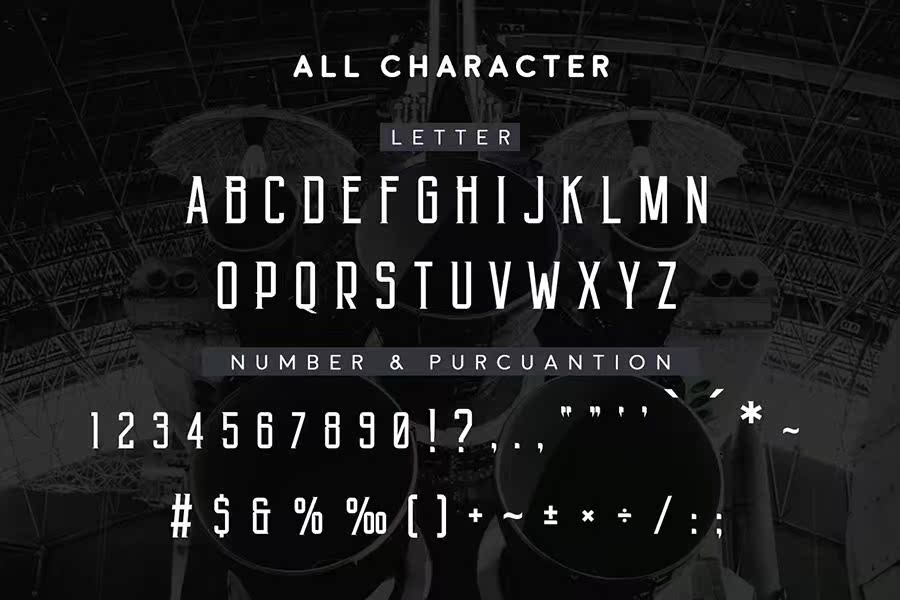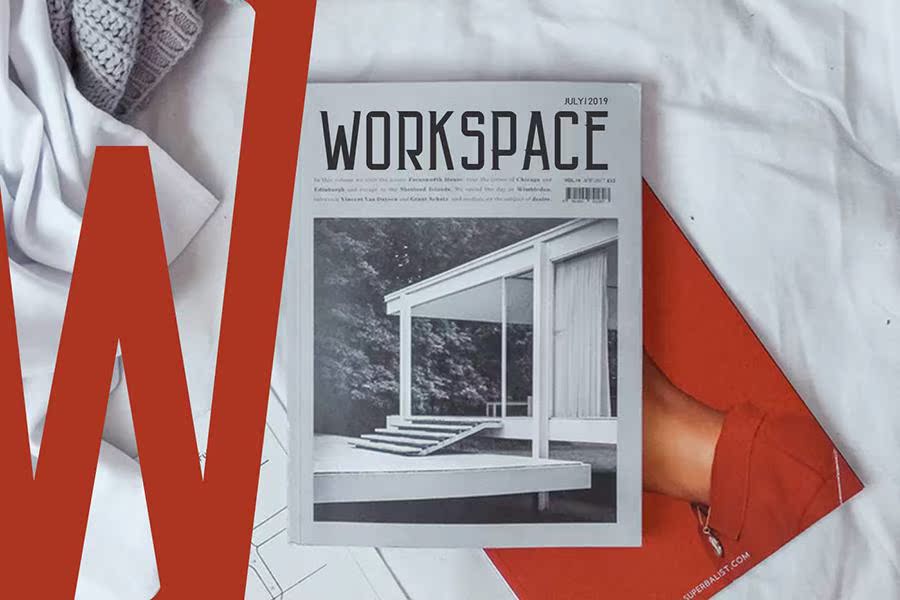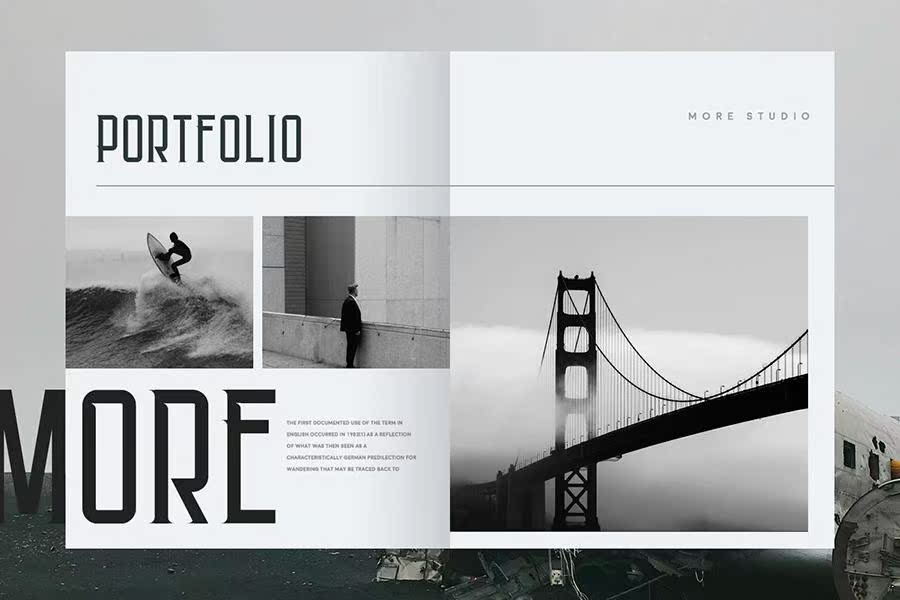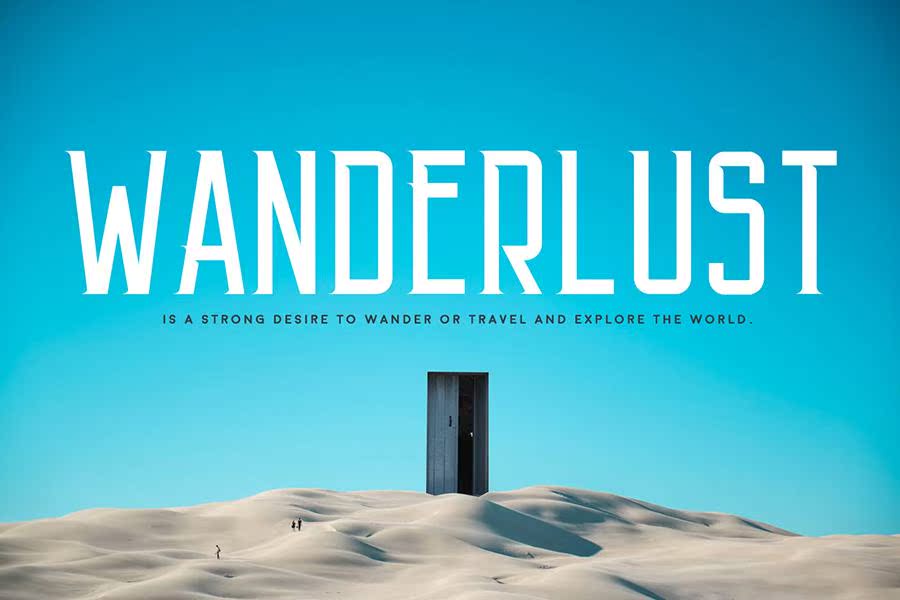
Angkasafree Display Font是一款现代简约风格的产品。这款精美的Ci Fifton以一种合法、经典和现代的外观为您的最新项目提供个性化的触感。这款FontOffers采用定制的图形设计,将完善任何不同的项目,包括徽标和品牌、邀请函、文具、社交媒体、广告、产品包装、产品设计、标签、摄影、,水印、特殊物品或任何需要的现代水印。